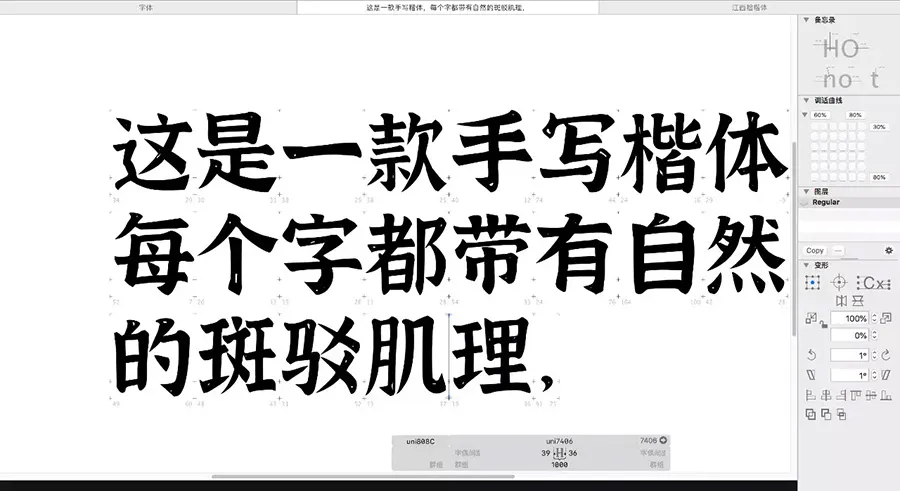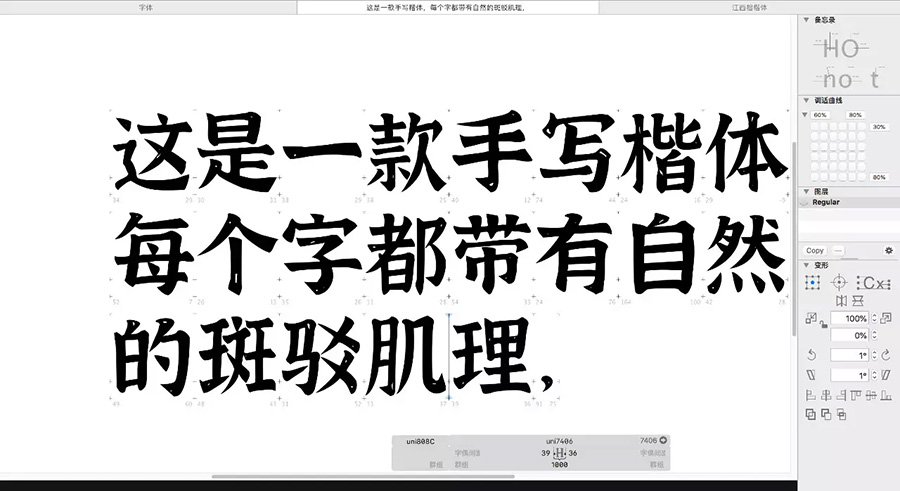
大家好,我是黃煜臣,我個人第一套字體,今天正式跟大家見面了。第一套字體的發佈我很重視,自己花了那麼大精力去做這件事,今天終於有了一個階段性成果,此時內心既有點小激動還有些忐忑,我不知道發佈後會有甚麼效果,大家是喜歡還是無感?會不會帶著期待而來,又失望而去?不過俗話說的好,醜媳婦終得見公婆,藏著掖著不敢露臉肯定是不行的,敢於直面不同眼光的評判才是勇敢者的做法,說不準會有人喜歡這個醜媳婦。
這套字體從手稿到成品,中間經過了無數次的修改調整,與最初字形相差挺大。對於這款字體的發佈,我不希望僅僅就是一款字體的展示,我希望它能發揮更大的作用,帶來一些其他的價值,為了達到這個目的我想了很久——最終決定用這款字體為我們大江西做宣傳。江西在各省市一直是一種低調的存在,不管是經濟發展還是對外傳播都是比較滯後的,我作為江西人,現在還沒有能力用真金白銀去為家鄉做貢獻,但是我可以用我的一點專業技能來為江西打打廣告,做做宣傳,希望讓更多人認識他,喜歡他。
這是一套手寫楷體,相比電腦中標準化製作的楷體,這套字體的筆畫會帶有一些書寫的痕跡,每個字的筆畫是沒有統一標準的,所以看上去顯得不夠規範,但是會有一種手寫的自然之感。這套字體從寫手稿開始到今天的最終成品,前前後後花了近半年時間,僅僅是調節點,就花了20多天,其中的滋味做過才知道。
你可以試試用這個字體來做印章,會有意想不到的效果,跟印章的斑駁肌理很契合。也可以試試用在文創產品上, 比如帆布袋,手機殼。這款字的性格和江西很像, 低調內斂,樸實無華毫不張揚!